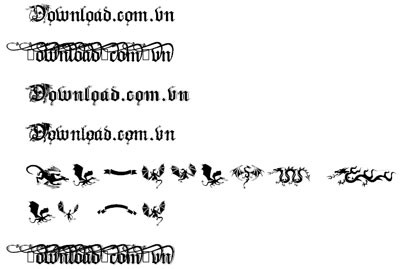
Khám Phá Bộ Font Drago Độc Đáo
Bộ font Drago bao gồm 7 phiên bản font chữ được thiết kế ấn tượng, hứa hẹn mang đến những trải nghiệm thị giác mới mẻ.
Cấu Thành Bộ Font Drago
Bộ font Drago được cấu tạo từ 7 font chữ riêng biệt, cung cấp sự linh hoạt và đa dạng trong quá trình thiết kế.
Điểm Nổi Bật Của Font Drago
Font Drago gây ấn tượng mạnh mẽ nhờ phong cách thiết kế độc đáo, phù hợp với nhiều xu hướng thiết kế khác nhau.
Font Drago có thể được ứng dụng trong nhiều lĩnh vực, từ thiết kế đồ họa đến thiết kế web, giúp tạo nên những sản phẩm chuyên nghiệp và thu hút.
• Câu hỏi: Bộ font Drago gồm những font nào?
• Trả lời: Bộ font Drago bao gồm 7 font khác nhau, mang đến sự đa dạng cho các dự án thiết kế của bạn.
• Câu hỏi: Bộ font Drago có đặc điểm gì nổi bật?
• Trả lời: Bộ font Drago được biết đến với thiết kế ấn tượng, tương thích với nhiều phong cách thiết kế khác nhau.
Câu hỏi thường gặp
Bộ font Drago bao gồm những font chữ nào?
Bộ font Drago gồm 7 font chữ khác nhau, giúp bạn có nhiều lựa chọn để tạo nên những thiết kế ấn tượng và đa dạng.
Font Drago có những đặc điểm nổi bật nào?
Font Drago được đánh giá cao nhờ thiết kế ấn tượng và khả năng ứng dụng linh hoạt trong nhiều phong cách thiết kế khác nhau. Đây là lựa chọn lý tưởng để tạo điểm nhấn cho các dự án của bạn.